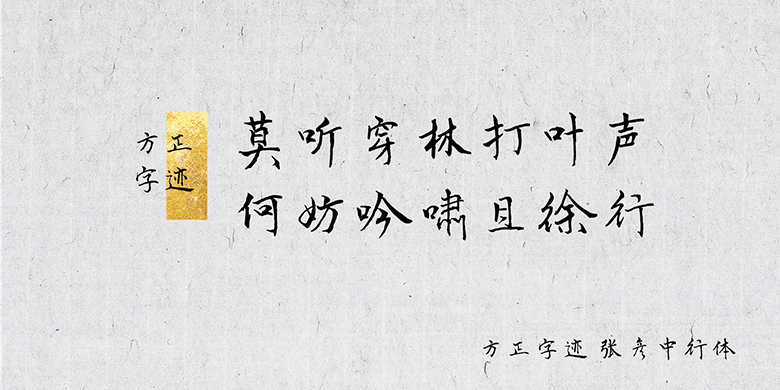
方正字迹-张彦中行体
方正字迹-张彦中行体,这款字体结构工整、笔画清晰,兼顾美观与易读性,适用于标题、正文、海报、包装、LOGO 等多种场景。字形优雅稳定,风格百搭耐看,适配日常排版与创意设计,让文字呈现更舒适、更具质感。方正字迹-张彦中行体一笔一画,皆是细节,以均衡的比例、流畅的线条打造舒适视觉体验,字形端正大气,风格简约现代。无论是商业设计、品牌宣传还是日常排版,都能轻松驾驭,让文字更有格调与力量。方正字迹-张彦中行体字体下载。
字体品牌: 方正字迹 设计师:张彦中 字体分类:常规书写·毛笔 字体属性:精品字 字符集:大陆简体(GB2312-80)、简繁扩展(GBK) 发布时间: 2019
《方正字迹—张彦中行体》本款字体秉承了“为天地立心,为往圣继绝学”的初衷,力求以中国书法正脉——二王(王羲之、王献之)、欧、颜、柳、赵的笔法、结体遵循,融入了作者张彦中多年研修书法的心得和时代特征,用小楷狼毫书写而成。
作为一款将在互联网数字时代被广泛应用的字体,“张彦中行书”字体兼具赏心、悦目、规范、灵动的特点,集辨识度、观赏性、实用性为一体,既体现通用性,又彰显文人个性。希冀融汇唐人的法度和宋人的尚意,为中文使用者提供一款实用和艺术兼备的文字样式。